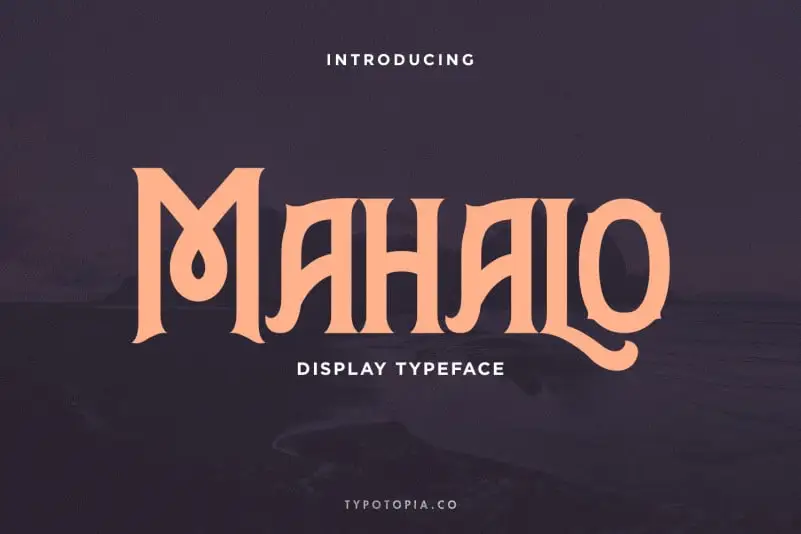
Mahalo Display Typeface – Download Grátis
A Mahalo Display Typeface é uma fonte tipo-display que surpreende com sua originalidade e interesse. Perfeita para seu próximo projeto criativo, seja ele uma marca, cartaz, um adesivo de produto ou até mesmo rótulos para embalagens, a Mahalo oferece uma sensação vibrante e inovadora à qualquer trabalho em design. Além disso, sua utilização como tipo logotipo ou carta de encaminhamento pode dar um toque único ao seu projeto, tornando-a não apenas uma opção versátil para várias aplicações gráficas, mas também uma escolha interessante e original. Combinada com a designer typotopia que criou essa fonte, você terá tanto recursos quanto criatividade necessários para transformar seus ideais em realidade.